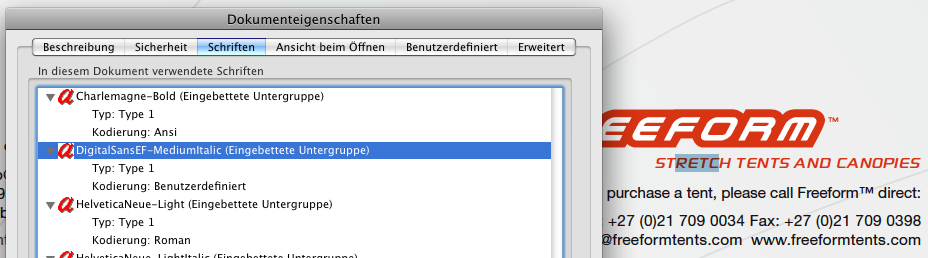
Zeichensatz in einer Homepage
Ich soll sozusagen die deutsche Version einer Internetseite bauen, kenne aber den Zeichensatz des Firmenlogos nicht.
Ich hoffe, hier kennt jemand den Namen und ggf. eine Bezugsquelle.
Das Logo stellt in ZA auch gleichzeitig das Hauptprodukt dar, was in Deutschland in verschiedene Produktgruppen aufgeteilt werden soll, die dann im gleichen Stil erscheinen sollen.
irgendeine grobe Schätzung würde mir schon reichen, scheint ja eine Monospace zu sein, wobei das schlecht zu erkennen ist, weil die Buchstaben sowieso gleich breit sind. Das M ist aber wohl typisch, sowas kenne ich nicht. :?
Die ist ähnlich:
Die passt besser (und sie wird vom Vertriebspartner verwendet):